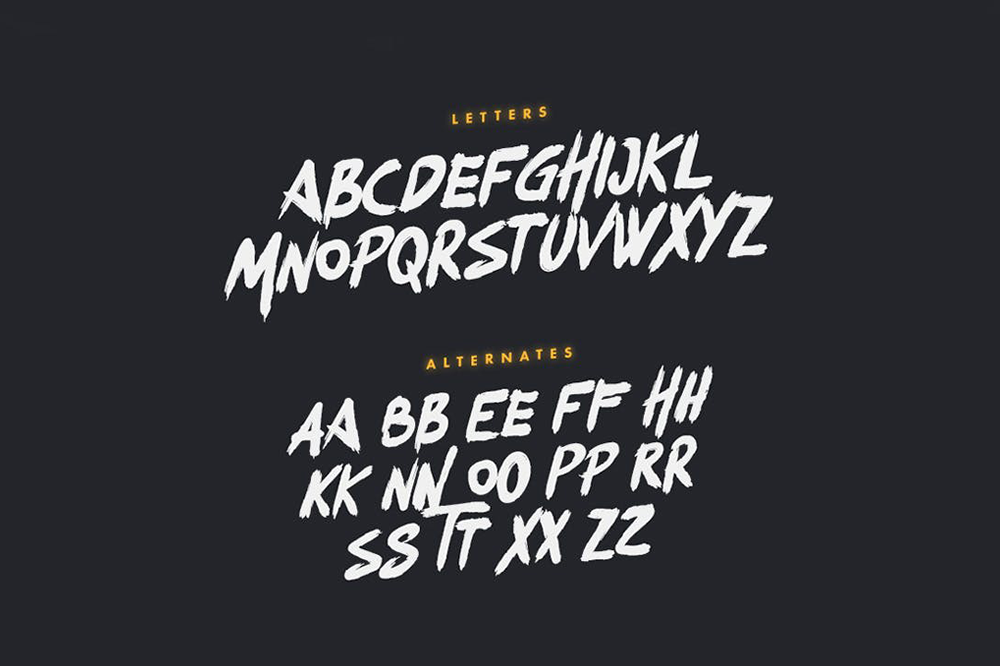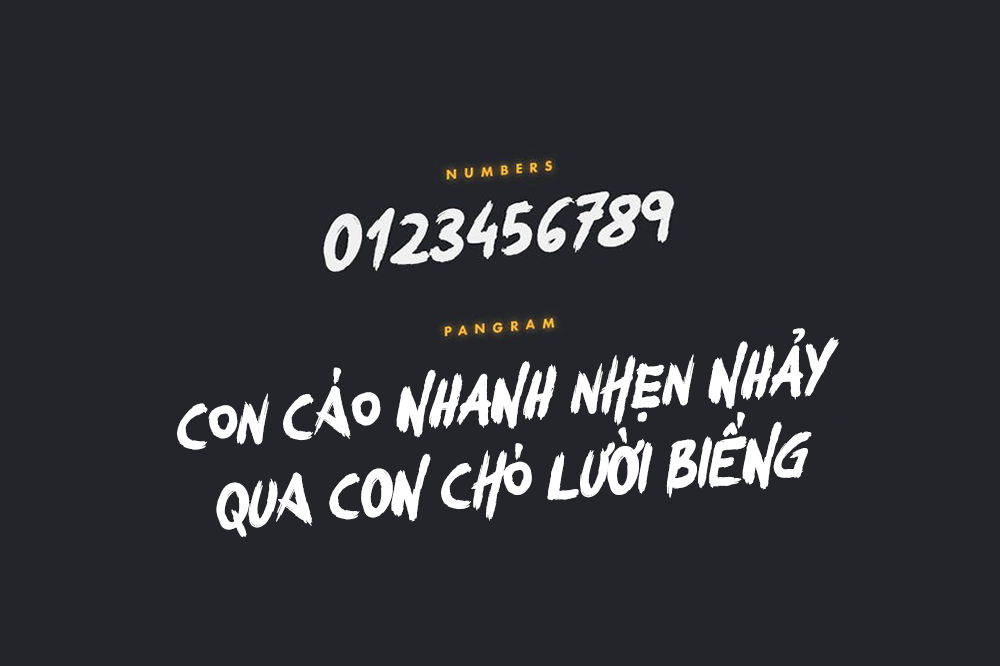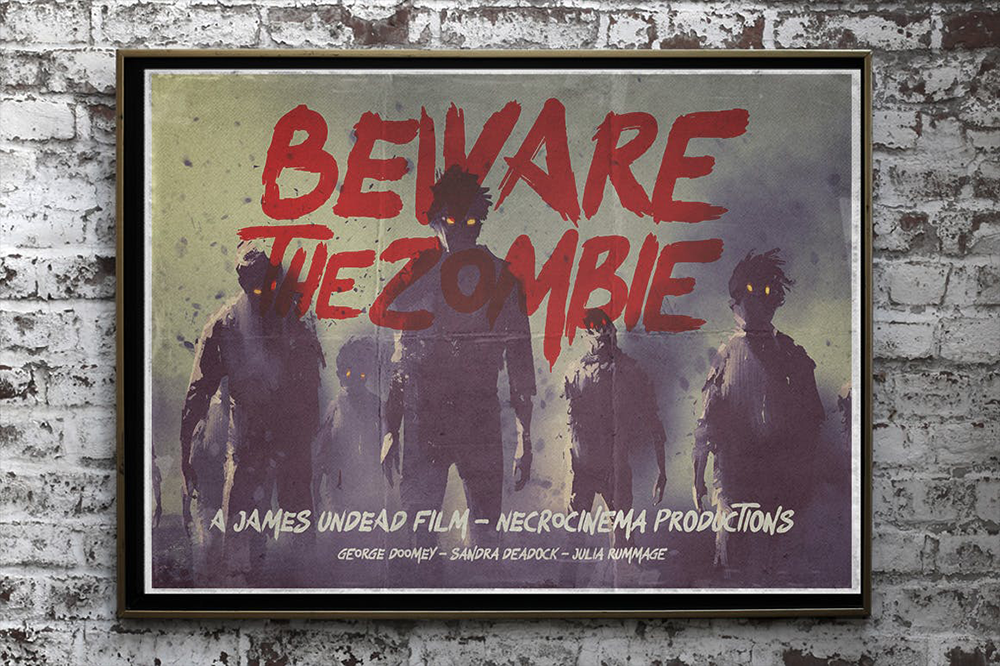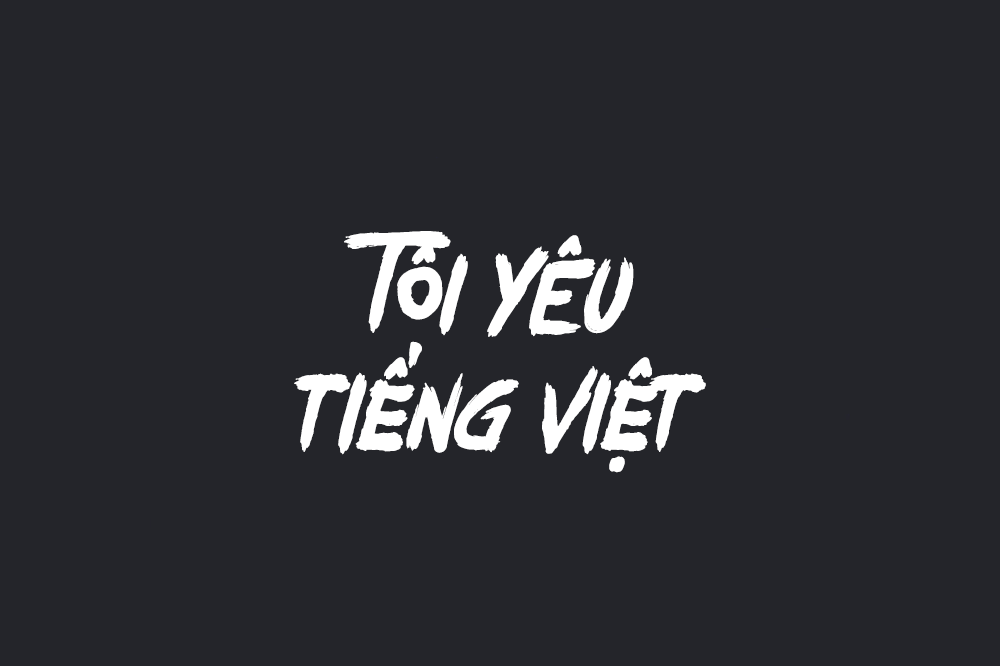
Okami là một font chữ cọ vẽ tay với các ký tự thô ráp và đậm nét. Font chữ này rất phù hợp cho logo, branding, các dự án in ấn và những tiêu đề cần thu hút sự chú ý. Okami bao gồm chữ hoa hỗ trợ đa ngôn ngữ, dấu câu và chữ số. Font cũng đi kèm các kiểu ký tự thay thế cho nhiều chữ cái, có thể bật/tắt thông qua phím Caps Lock.
Nhà thiết kế: Tugcu Design Co.
Nhà phát hành: Tugcu Design Co.